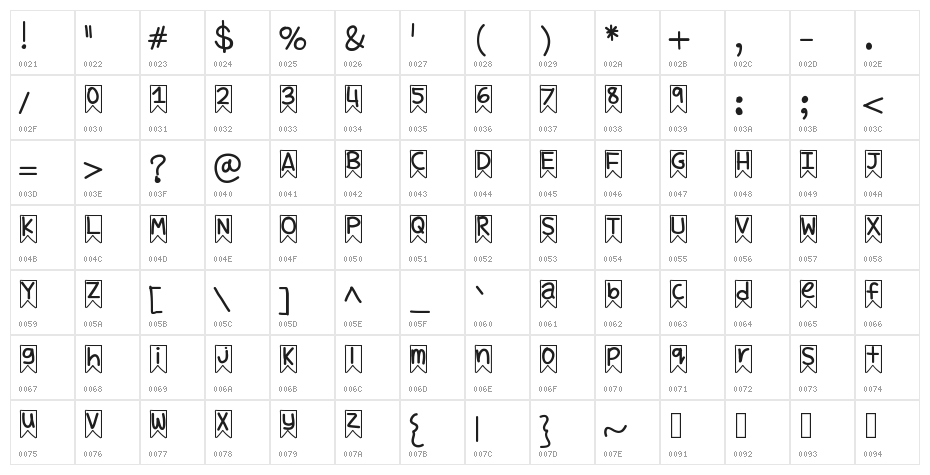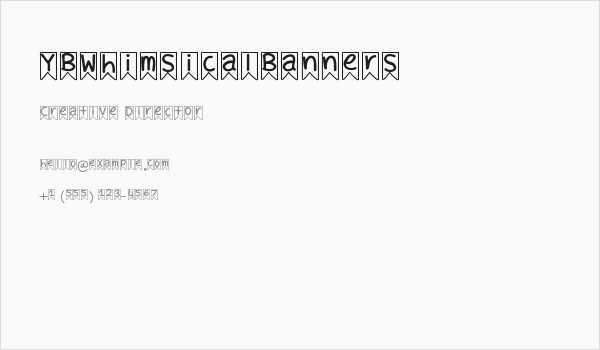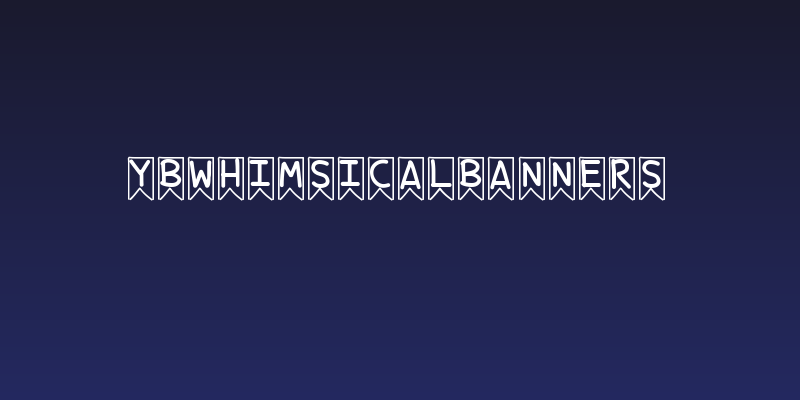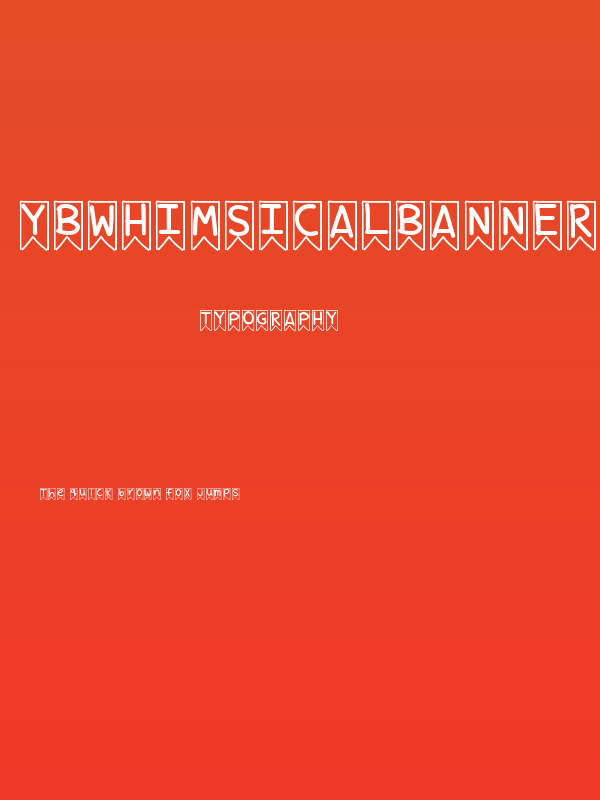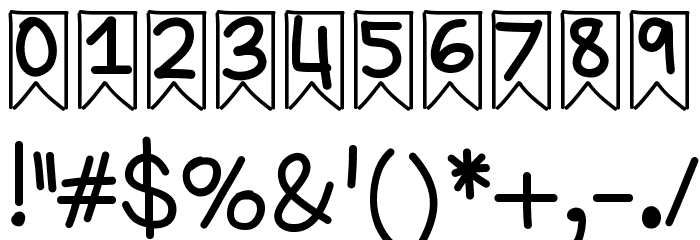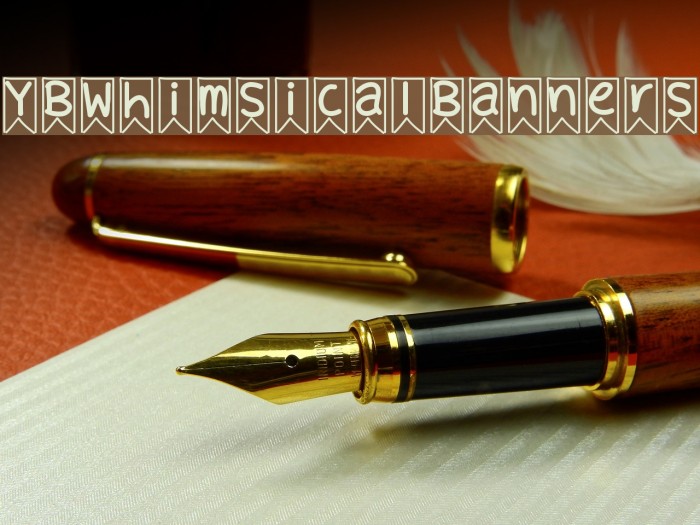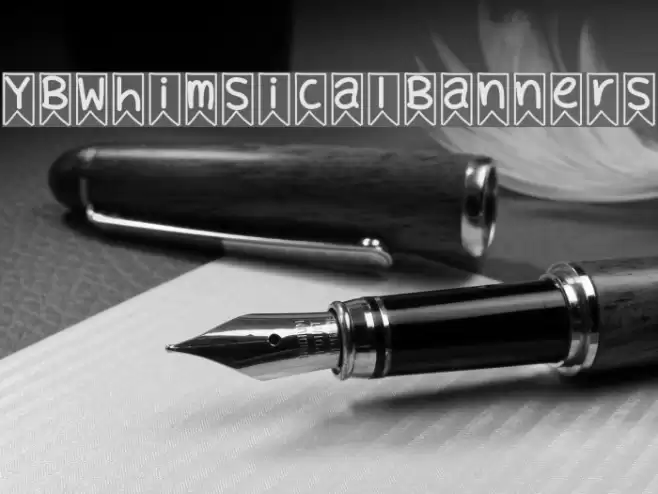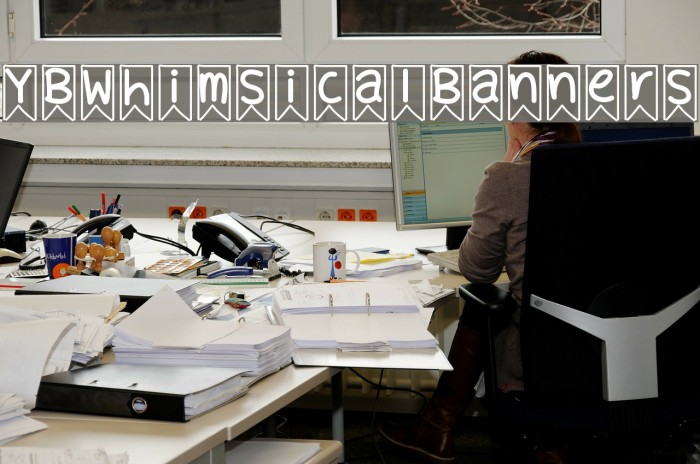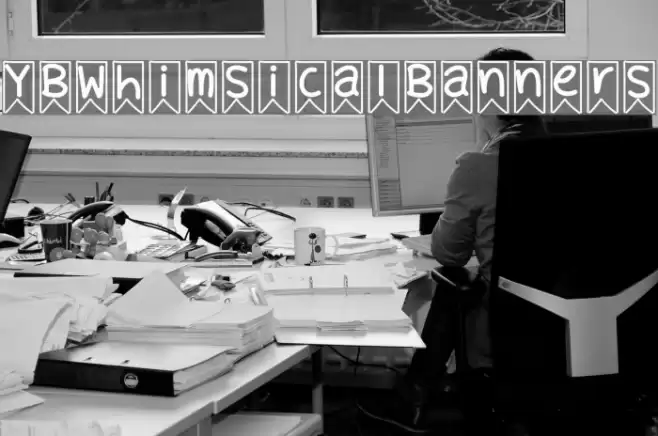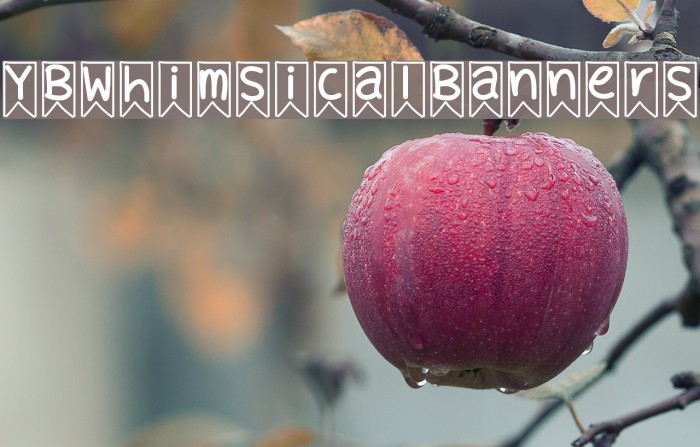
YBWhimsicalBanners Font
| Cas d'utilisation | Headlines, Logos, Invitations |
| Projets proposés | Ideal for party invitations, children's book covers, festive banners, and creative branding projects. |